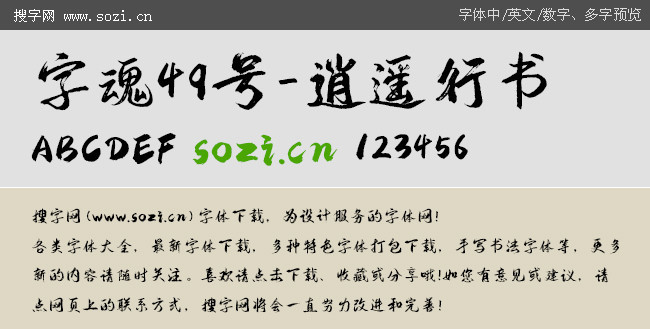
字魂49號(hào)-逍遙行書
搜字網(wǎng)提供一款字魂49號(hào)-逍遙行書中文字體下載,該字體是一款毛筆書法手寫字體,該字體包含6763個(gè)中文、字母、 符號(hào)和數(shù)字,具有古典、中國(guó)風(fēng)、婉約、手寫風(fēng) 的風(fēng)格,可以滿足您設(shè)計(jì)上的各種需求,該字體主要用于企業(yè)店鋪、標(biāo)志、導(dǎo)視、印刷品 等場(chǎng)景。